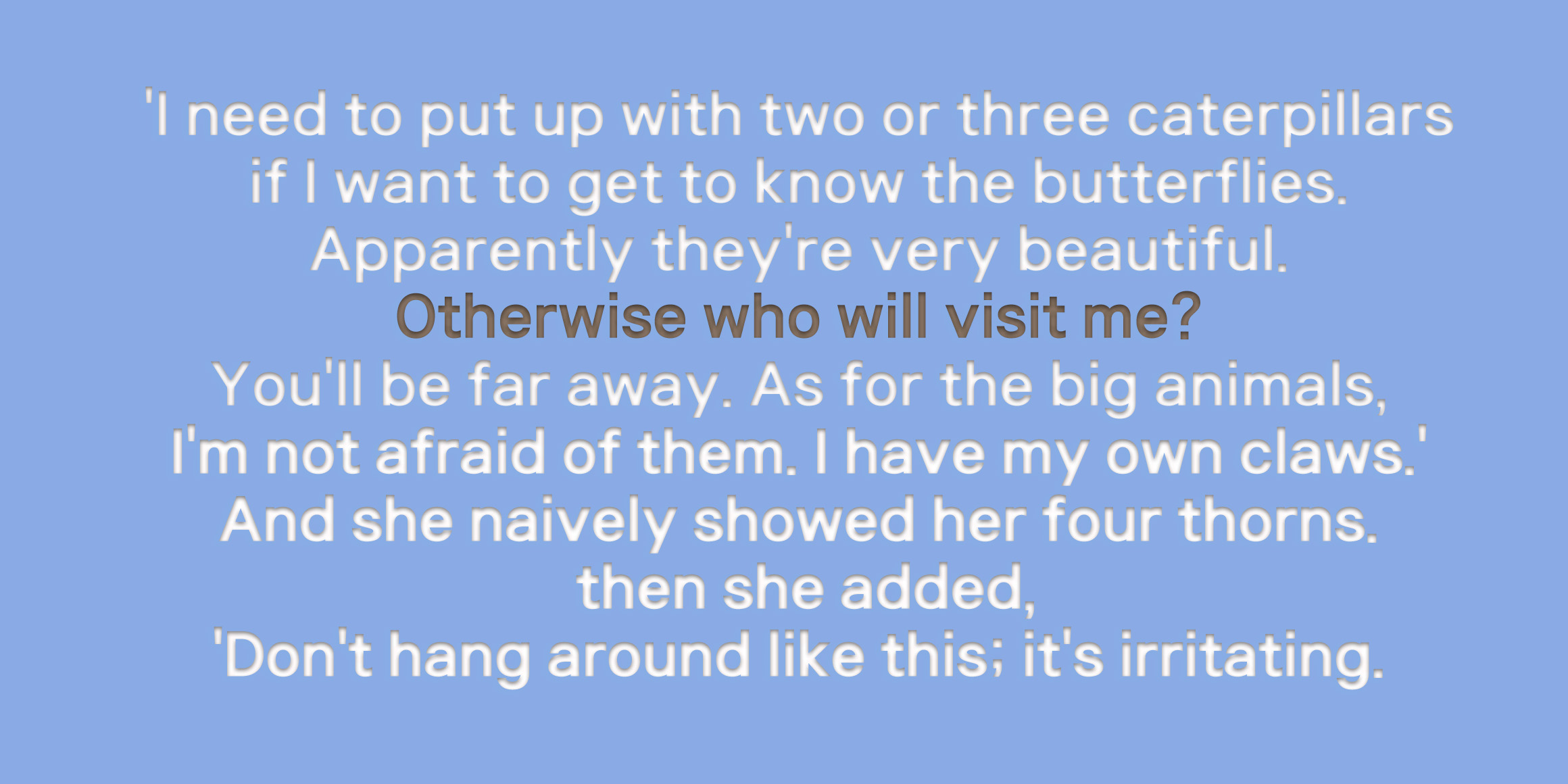
Sandoll 아람
산돌 아람은 산돌 아트의 직선적인 모습에 좀 더 부드러움을 강조한 폰트이다.
기본적인 형태가 기하학적이고 현대적이라 고딕체 대신 많이 사용되며, 아트체와 같은 모듈이지만 직선적인 모서리 부분을 부드러운 곡선으로 처리하여 아트체와 차별하였다.
Sandoll 아람